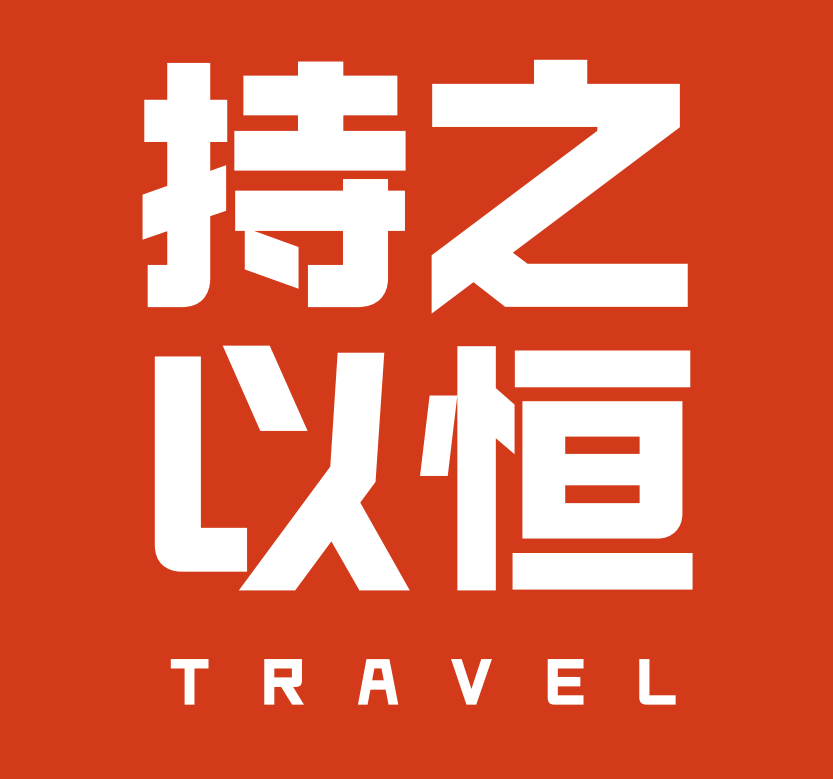
现代年轻人更喜欢搞钱?抓住年轻人痛点的新生态字体
励字造梦字库为年轻人定制的新生态字库品牌,将奇妙的灵感交锋、夸张的个性表达,融合在一笔一划中,让人人都可以成为造字侠,让更多热爱汉字设计的人,实现造字梦想。
励字志向黑采用圆体与黑体的融合,在笔画拐角增加适当的外圆角的手法在整体稳重大气的字形中增添少许灵动,使字体字面充实,结构稳定之余,更适配屏显的使用。